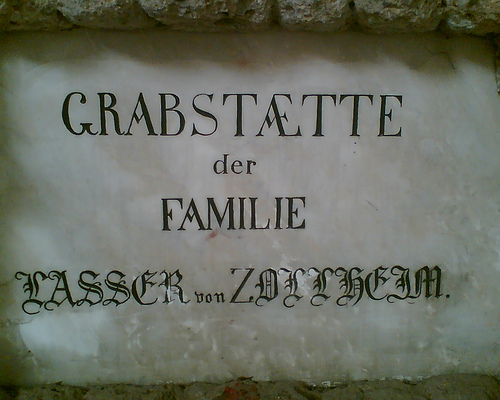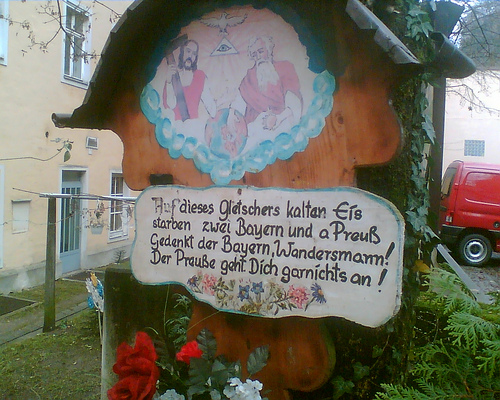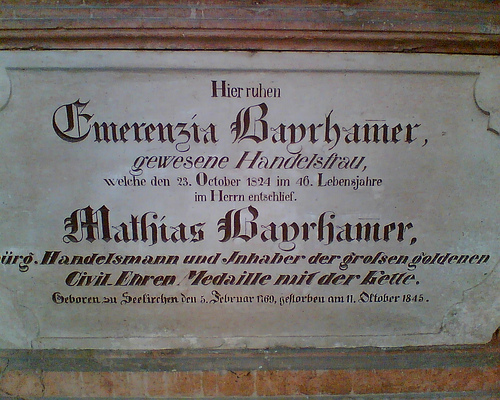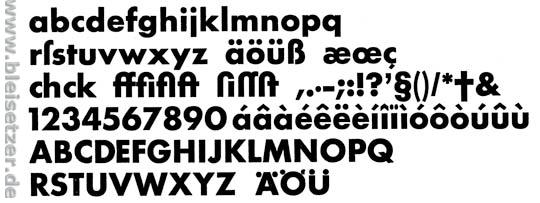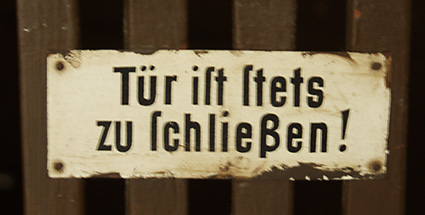
Historische Typographie
Ich bin gerade in meinem Photoalbum über ein paar Aufnahmen gestolpert, die ältere Typographie zeigen, die so heute nicht vorkommen würde, aber ihren ganz eigenen Charme hat:
Hier ist die 1 besonders bemerkenswert, auch die Abteilung innerhalb der Bibelstelle mit Doppelpunkt, die wir heute im englischen Sprachraum finden, hierzulande eigentlich nicht (mehr).
Selbst Orthographie und Satzbau haben ihre Eigenheiten; geschlampt wurde freilich auch damals schon, wie das Loch hinter »84.« zeigt.
Der Umlaut wird in außerhalb der Fraktur heute kaum in dieser Form zu finden sein, selbst in der Fraktur selten. Es gibt einen Schnitt der Alten Schwabacher mit solchen Umlauten, ich bin mir aber nicht sicher, ob auch digital. Bemerkenswert ebenfalls das Lang-s im Antiquasatz, besonders in der Kombination Lang-s-Schluß-s in »Weiss«. Dies ist so selten, weil es diese Kombination im Deutschen bis zur Abschaffung der Rechtschreibung überhaupt nur in Eigennamen geben konnte, sonst hätte dort eigentlich in allen denkbaren Worten ein ß hingehört.
Überhaupt hat diese Englische eine wunderbare lebendige Leichtigkeit und ist gerade durch ihre offensichtliche Unvollkommenheit DTP-Schriften überlegen, die bei ähnlichem Duktus vergleichsweise steril wirken.
Den Lang-s-Satz finde ich auch in Groteskschriften immer wieder schön und freue mich jedes mal, wenn mir ein Beispiel begegnet:
Renners Futura hatte meines Wissens auch noch beide s-Formen, spätestens bei der Rechneradaption ist dann die eine unter die Räder gekommen.
Ja, das ist richtig. Alle Futura Bleisatz-Schriften, die vor 1941 gegossen wurden, hatten das Lang-s im Zeichensatz. Nach dem Krieg wurden die Lang-s dann nicht mehr mit ausgeliefert. Ich müßte mal bei Stempel nachfragen, ab wann genau nicht mehr. Ich meine gelesen zu haben, daß die Standard-Gußbelegung irgendwann damals neu festgelegt wurde.
Hier ein Andruck einer alten Futura fett inkl. Lang-s nebst entsprechender Ligaturen. Sieht hübsch aus, nicht?
Ja, das Teil hätte ich auch unter viewtopic.php?f=1&t=4887 posten können, aber hierher gehört es auch — wegen der Substitution des I durch ein J. Das war wohl mal eine typographische Mode, oder besser gesagt: Unsitte. Man sieht es öfter im Versalsatz vom Anfang des 20. Jahrhunderts. Weiß jemand darüber näheres?
Substutution des I durch ein J. Das war wohl mal eine typographische Mode, oder besser gesagt: Unsitte. Man sieht es öfter im Versalsatz vom Anfang des 20. Jahrhunderts.
Die Süddeutsche Zeitung hat das auch bei den in Grotesk gesetzten Überschriften so gemacht. Aber inzwischen scheint man sich das glücklicherweise abgewöhnt zu haben.
Bis wann haben die das gemacht?
Weiß ich leider nicht, aber ich glaube, die Umstellung ist noch nicht länger her als gefühlte zwei oder drei Jahre.
Das gibts auch immer noch. Und zwar z.B. in der FF Schulbuch Süd.
Hab dies erst unlängst in einem Kinderbuch entdecken müssen, das ich meinen Kindern vorgelesen habe. Das war aus diesem Millennium. Schrecklich. Den Titel hab ich gleich verdrängt. Und auf Grund des Namens vermute ich dass dies eine geographische Verirrung ist. Aber keine österreichische, wie ich meine.
Aber keine österreichische, wie ich meine.
Wenn ich mir einige österreichische Schulbücher ansehe, kommt da des öfteren die FF Schulbuch Nord zum Einsatz (die eben dieses *Ding* nicht hat).
Schöne Idee übrigens mit historischen Typobeispielen.
Darf ich mich beteiligen?
In den Weihachtsfeiertagen spazierte ich auf einem kleinen Friedhof der Stadt Salzburg herum, dort wo angeblich auch Paracelsus seine Grabstätte haben soll, direkt unterm Mönchsberg – und hab zwei Bilder mitgenommen. (Mehr konnte ich nicht machen ohne meine Familie zu verärgern).
Bild 1:
4144194957_508e4b06b2.jpg
Abenteuerliche Schriftmischungen. Und funky ß, finde ich. Moment, das ist ja gar keines. :shock:
Versaliensatz in der Fraktur war damals auch schon schwer lesbar. Und ist da für ein Fraktur-Z das Geld ausgegangen?
Und als Abschluss noch eine sehr versteckte Gedenktafel in einem Hinterhof:
4144194493_5d69cd9e38.jpg
Text:
Auf dieses Gletscher kalten Eis
starben zwei Bayern und a Preuß
Gedenkt der Bayern, Wandersmann!
Der Preuße geht dich gar nichts an!
:D
He, Georg! War nur Spaß!
Weiß ich leider nicht, aber ich glaube, die Umstellung ist noch nicht länger her als gefühlte zwei oder drei Jahre.
Wenn Du irgendwo noch so eine alte SZ im Kellerregal oder sonstwo findest, wäre es schön, das hier zu dokumentieren.
((und eigentlich ist das keine Typografie sondern angewandte Schrift, bzw. lettering))
Das kommt eben darauf an. Vielleicht hatten die ja auch Pappalphabete, die dann auf den Stein kopiert wurden. Der Otto-Maier-Verlag hat solche Vorlagen ja auch für Maler herausgebracht (ab wann eigentlich?), so daß davon auszugehen ist, daß es auch solche Vorlagen für Steinmetze gegeben hat. Dann wäre es auch Typographie (im weiteren Sinne).